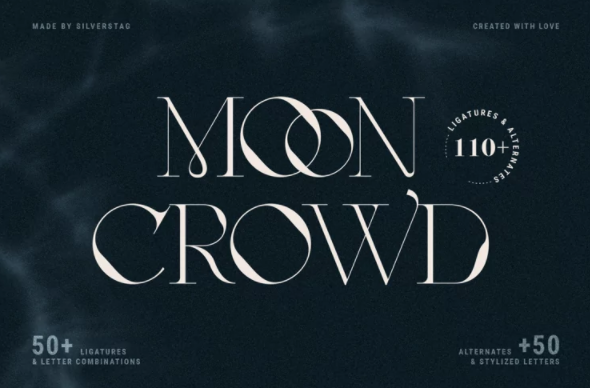
[Fontbundles] Moon Crowd Font (2021)
Привет, ребята, я очень горд представить вам MOON CROWD, новый лигатурный шрифт с засечками, вдохновленный непревзойденной элегантностью и красотой моды! Мой новый шикарный шрифт включает в себя более 100 лигатур и альтернативных букв. Каждая из стандартных букв, лигатур и альтернатив была сделана вручную, чтобы соответствовать другим буквам без исключения. Все буквы на 100% уникальны с мягкими закругленными краями, которые придадут вам иной вид, чем любой другой шрифт с засечками.
Итак, есть ли у вас клиент, которому нужен новый шикарный логотип, или вы оформляете свои посты в социальных сетях. Может быть, вы готовите свадебное настроение, канцелярские принадлежности, приглашения, шрифт MOON CROWD Ligature просто идеально подходит для всего этого и даже больше. Посмотрите фотографии, которые я подготовила для вас, чтобы увидеть, что вы можете с ним сделать, и счастливого творчества!